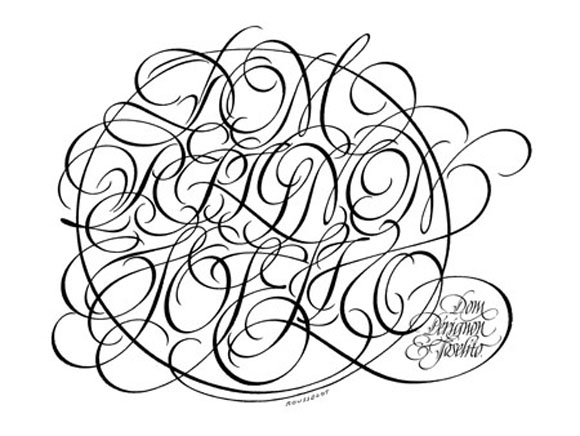
El prestigioso calígrafo y diseñador gráfico Ricardo Rousselot imparte unos cursos de caligrafía. Una buena oportunidad de aprender de un gran maestro.
Al respecto Ricardo nos aclara:
Hace ya varios años que me piden visitar escuelas y dictar talleres o conferencias sobre mi formación como calígrafo y la aplicación de esta herramienta en el diseño gráfico. Desde que comencé a trabajar utilicé el trazado de letras para realizar, tanto la imagen corporativa de una empresa como el packaging para un nuevo producto. Hace tiempo que los oyentes de aquellas conferencias me preguntan por workshops o seminarios, los pedidos se van sumando y he decidido armar una serie de workshops intensivos para aquellos interesados en el mundo de la caligrafía y sobre todo de la pasión por las letras. Como toda especialización necesita disciplina y de conocer muy de cerca los estilos históricos, deben ser aprehendidos para luego alejarse y experimentar.
La serie de cursos los he organizado para que puedan ser accesibles a todos los interesados; tanto para aquellos que recién se encuentran con la primer gota de tinta como para los que buscan especializarse y seguir recorriendo el trazo.
| Con diferentes herramientas obtendremos diferentes tipos de trazos. Conoceremos los efectos de cada una y construiremos otras. | |||||
| Cancilleresca gestual (parte I) Curso de especializaciónCon un curso no alcanza, este estilo considerado atemporal llega a nuestros días reinterpretado por miles de calígrafos de las maneras más originales. Cruzando los límites de la pauta, optando por nuevos soportes y herramientas pero manteniendo la esencia del estilo se obtiene un nuevo estilo fresco, libre, etc. una herramienta interesante para el diseñador gráfico cuando tiene el encargo de una marca o un packaging. Para aquellos que ya indagaron en la cancillerezca formal, este taller completa y amplía el uso de este estilo. |